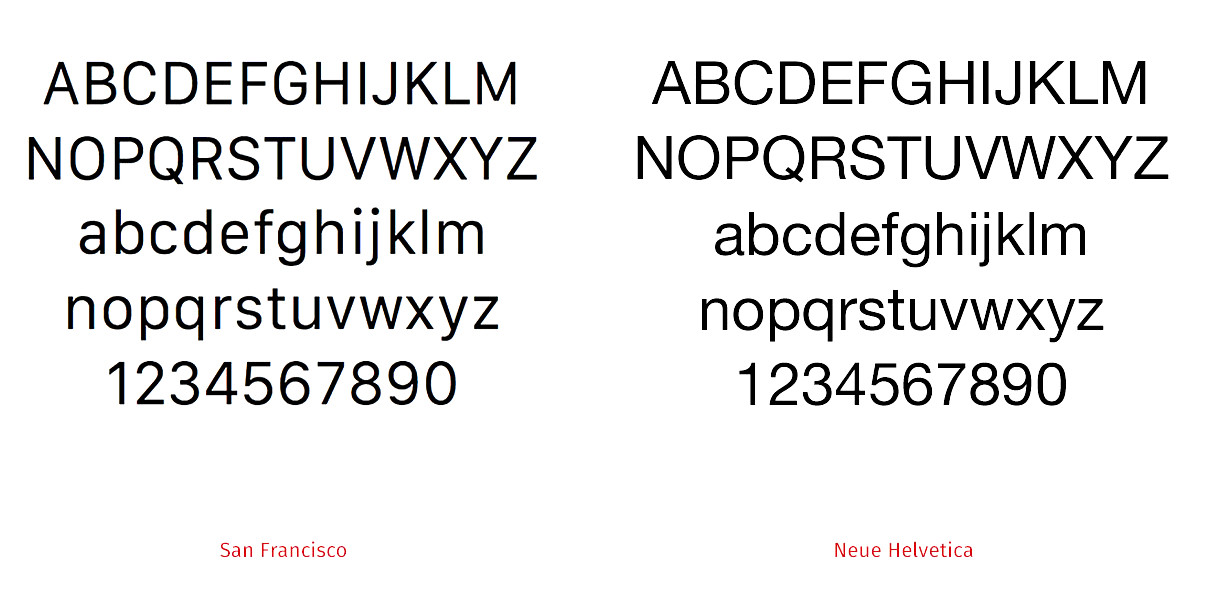
San Francisco utvecklades först av Apple för Apple Watch, men företaget har nu valt att börja använda det som typsnitt i sina andra produkter också. Som exempel levereras Apples nya 12-tums Macbook med San Francisco, samt Mac Os X El Capitan som släpps 30 september.
Enligt Apple är bytet till San Francisco en del av ett projekt i att använda en ”konsekvent typografisk röst” i alla Apples webbplatser och enheter.